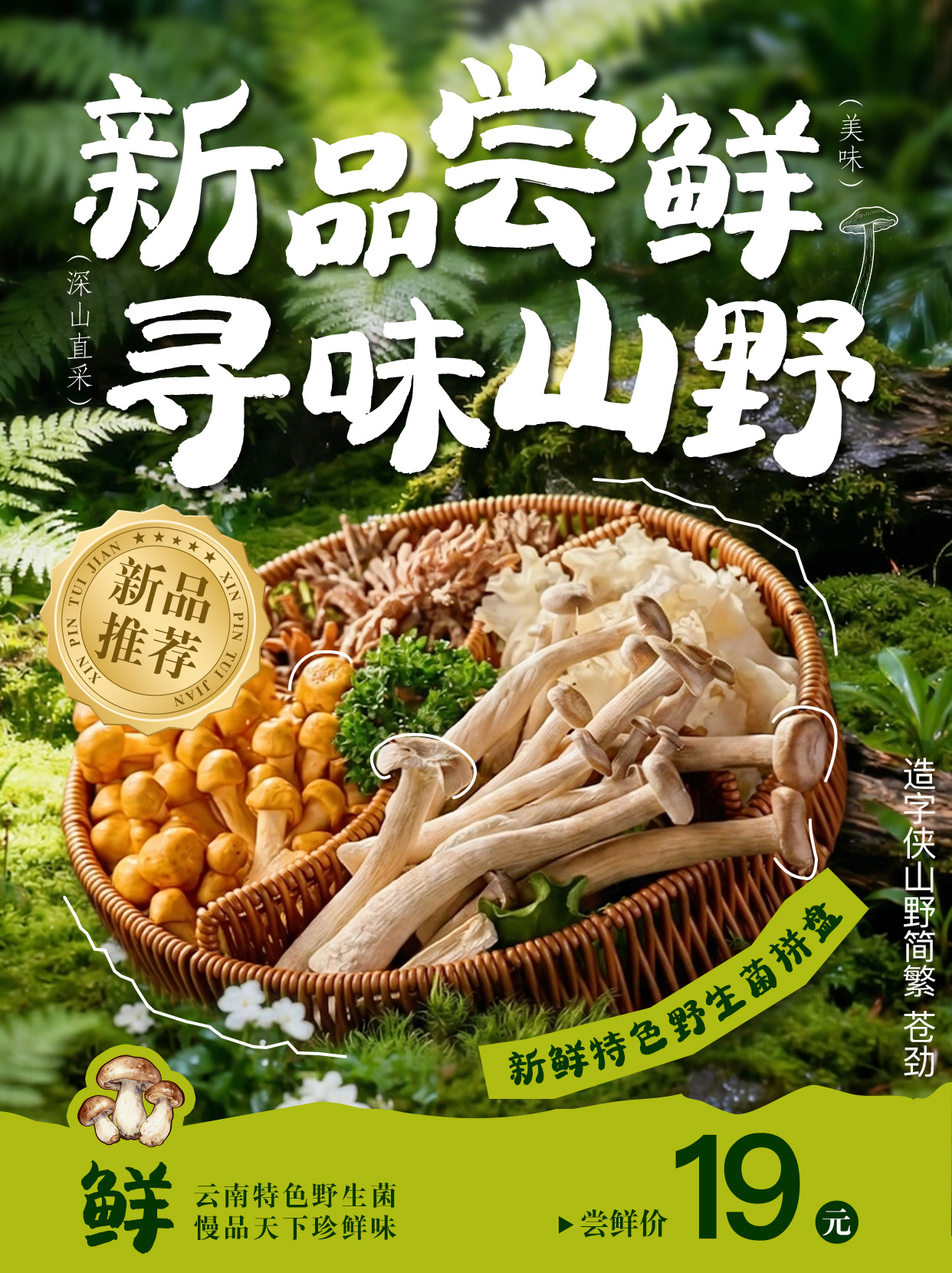
造字侠山野简繁 苍劲
PlayFont-ShanyeGBT-Black
山野为幕,绿意作裳
造字侠山野简繁 苍劲是一款创意手写字体,它的字面宽大,整体结构有右侧凸出的弧度,笔画稚趣可爱,并从上往下愈发粗厚圆润,营造出既醒目吸睛又温暖质朴的视觉效果。适用于海报设计、文创产品、品牌标识、包装等多种场景。